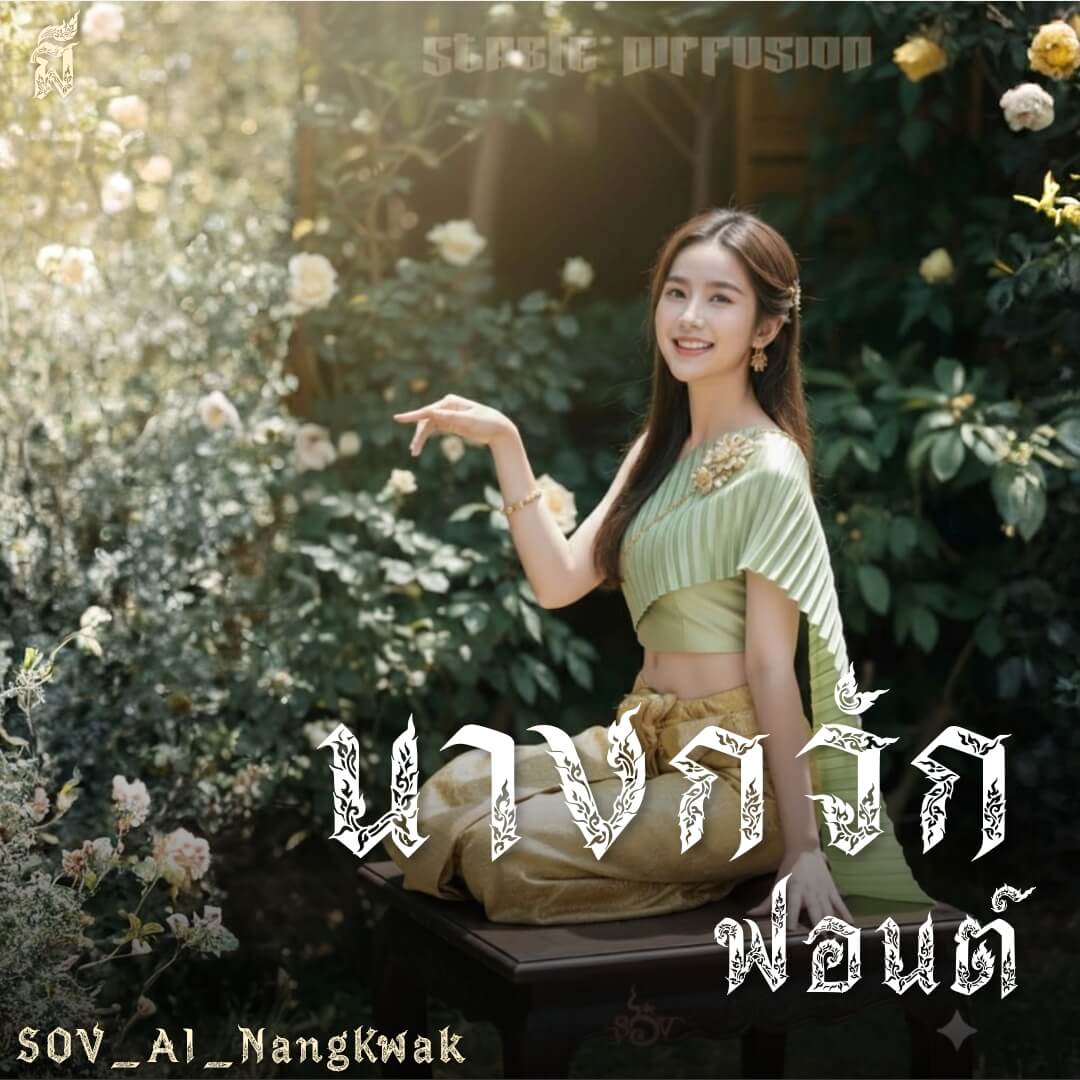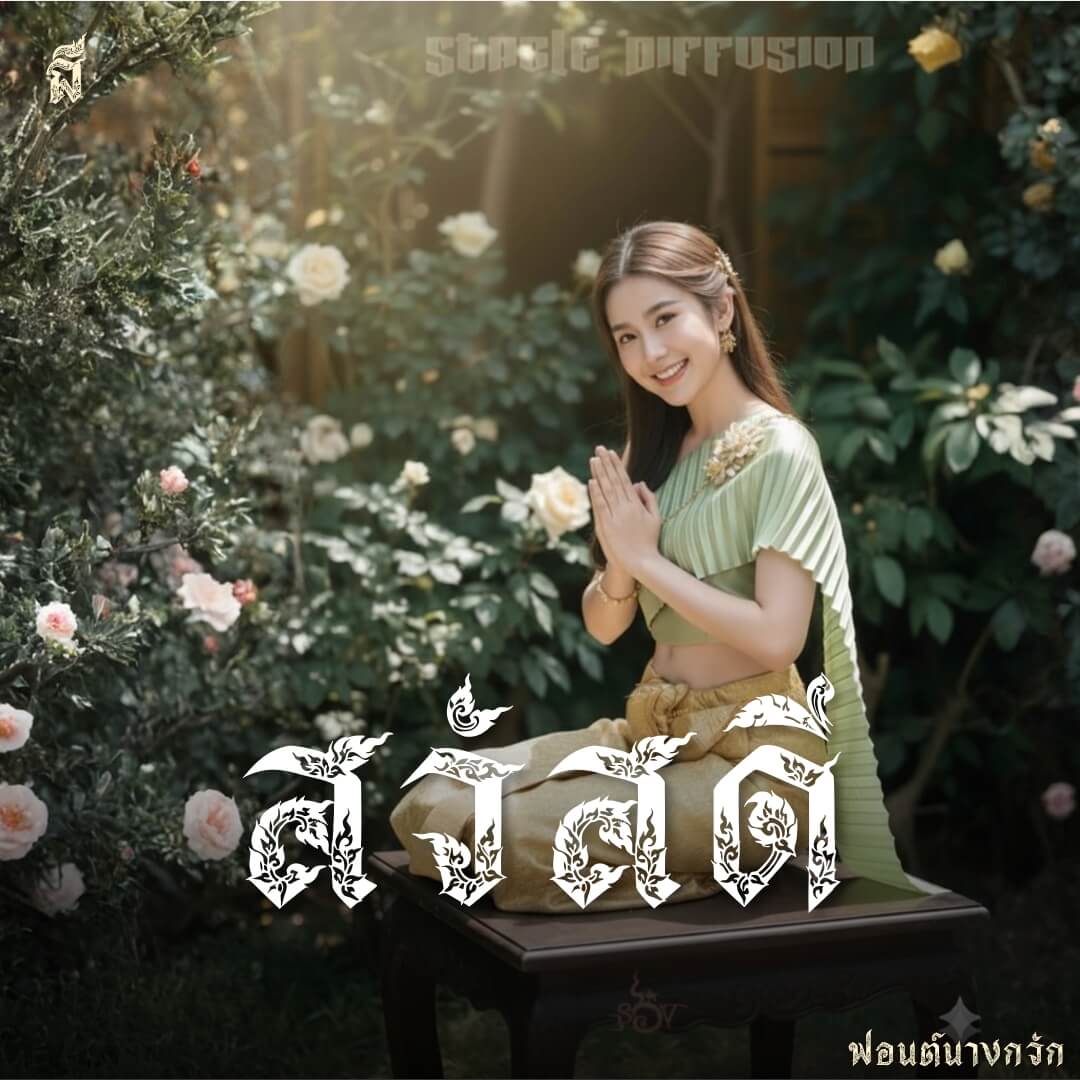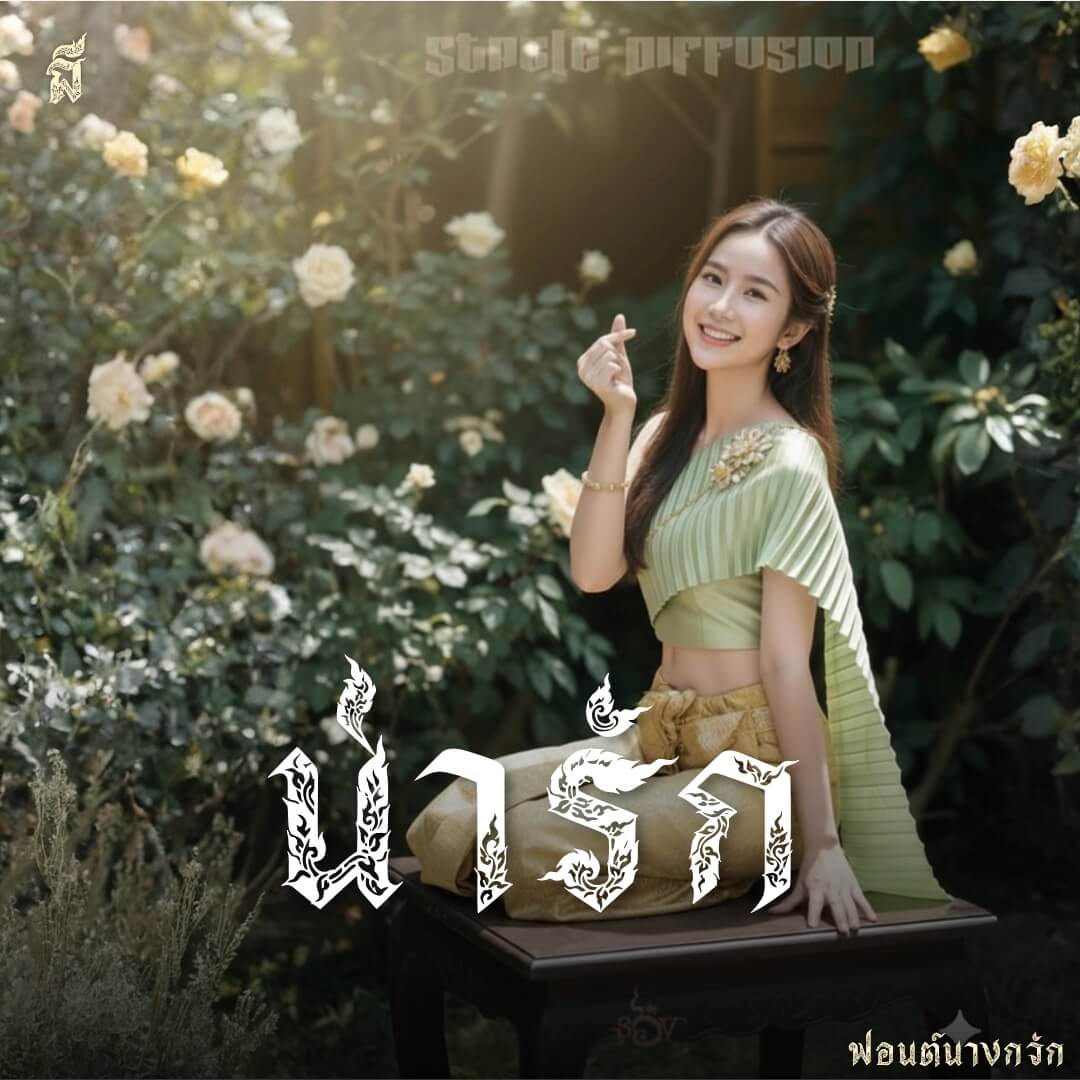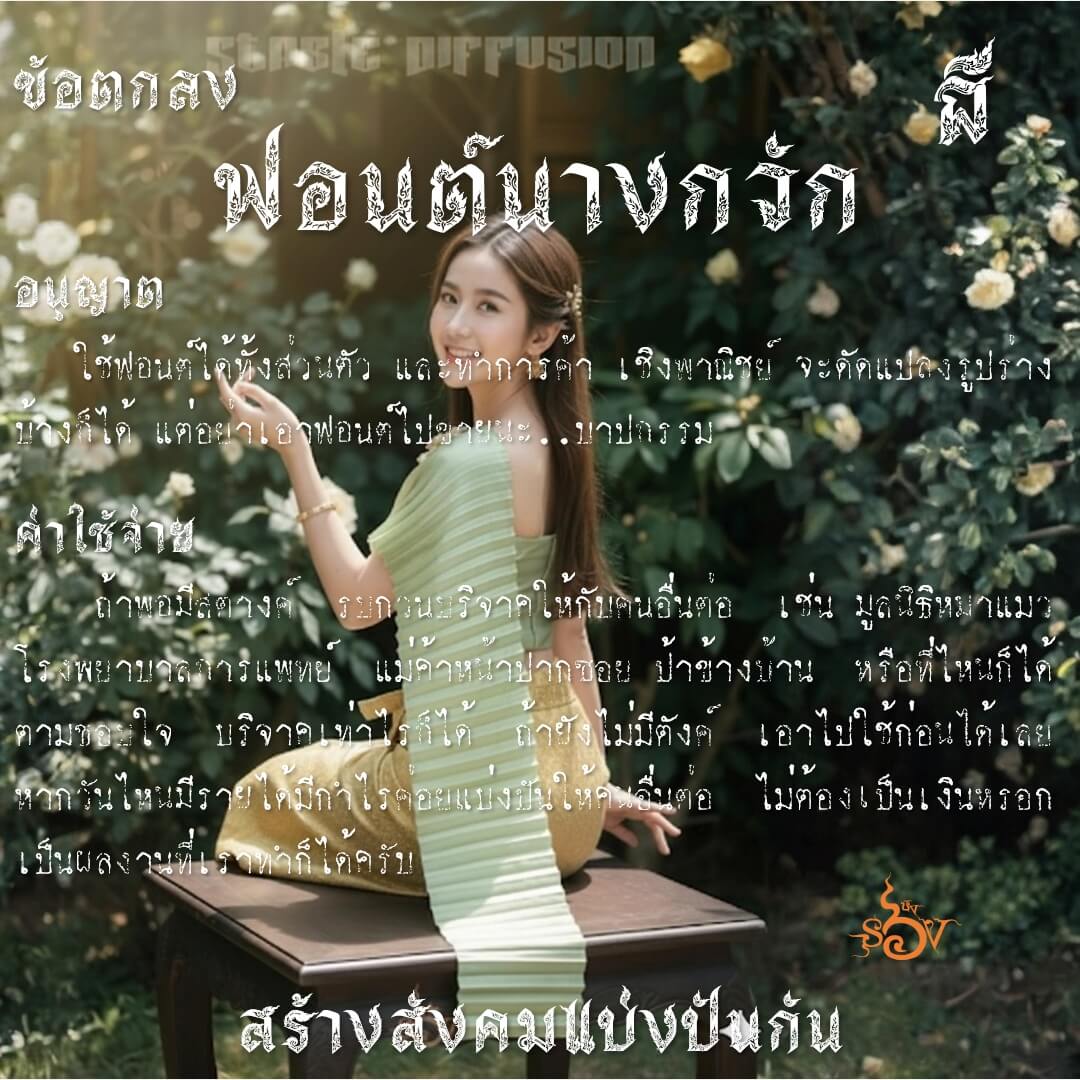
นางกวัก – ได้ชื่อมาจากคำชี้นำตอนที่ให้ AI gen รูปนางกวัก เป็นจังหวะที่ทดลองให้ AI ผสมลายกับฟอนต์ของเรา ..มั่วๆ จนได้รูปแบบอักษรเหลี่ยม ที่มีลายฉลุ และเส้นลายด้านนอก มารูปนึง ..จึงเอามาต่อยอด ทำเป็นตัวอักษรจนครบ
เบื้องหลังการออกแบบ : ฟอนต์ นางกวัก
นางกวัก (SOV_AI_NangKwak)